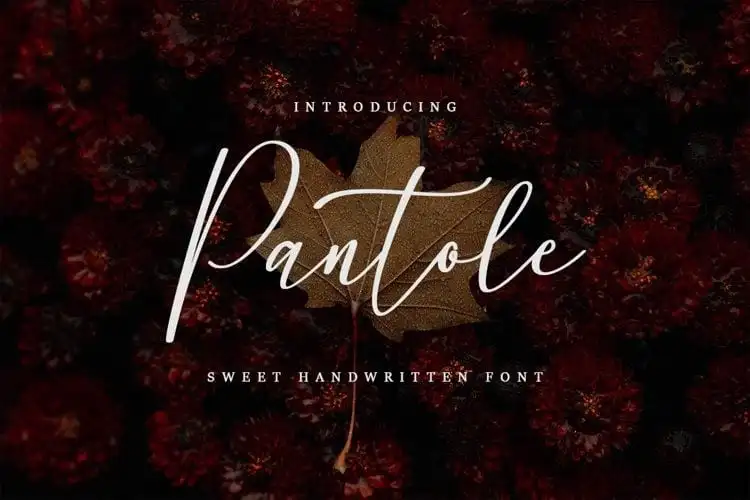
Pantole Script Font – Download Grátis
A ‘Pantole Script Font’ é uma nova variação de um tipo de fonte script feita à mão. Esta introdução completa sua coleção de fontes script, criada pelo designer Dav Studio na 99designs. Este tipo de fonte adquire a delicadeza e a vivacidade do traço manual, com formas elegantes que capturam o coração dos designers. É perfeito para diversas aplicações como desenhos de projeto, logotipos, cartões de visita ou qualquer trabalho onde desejas um ar pessoal e sofisticado em tua criação visual. Em sua riqueza de detalhes e simplicidade ao mesmo tempo, a ‘Pantole Script Font’ traz uma sensação única para o seu trabalho gráfico.